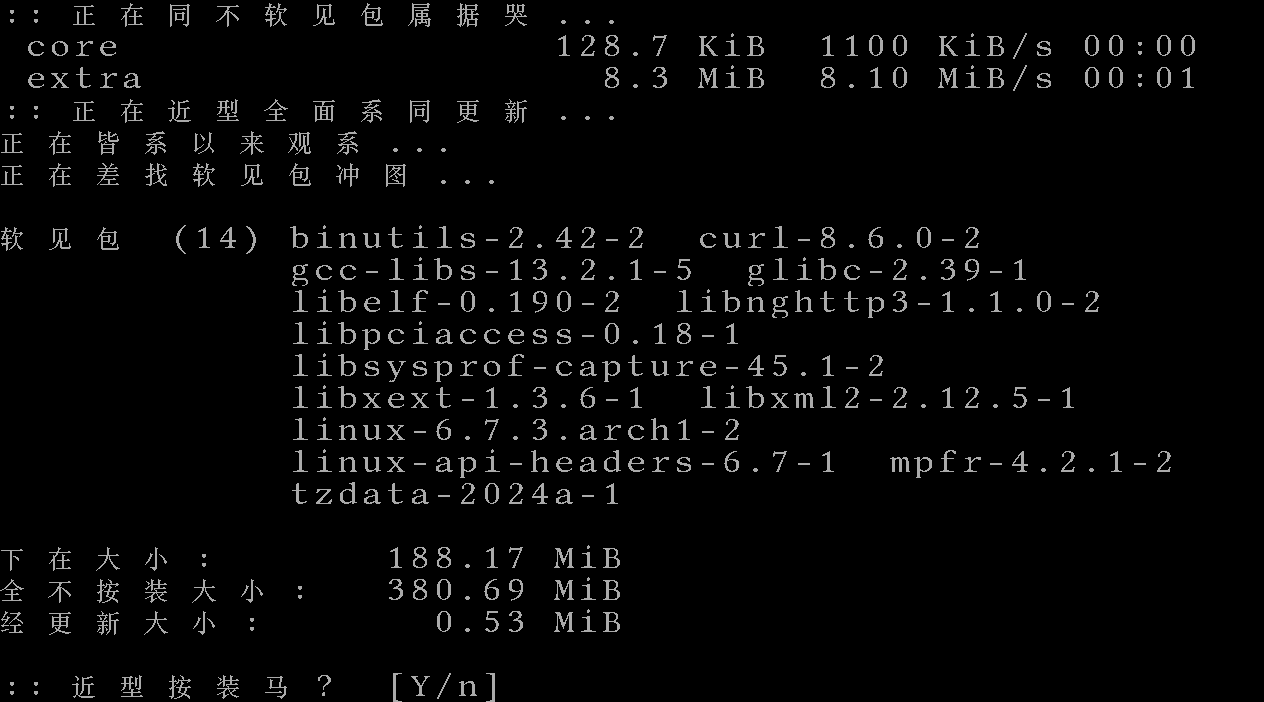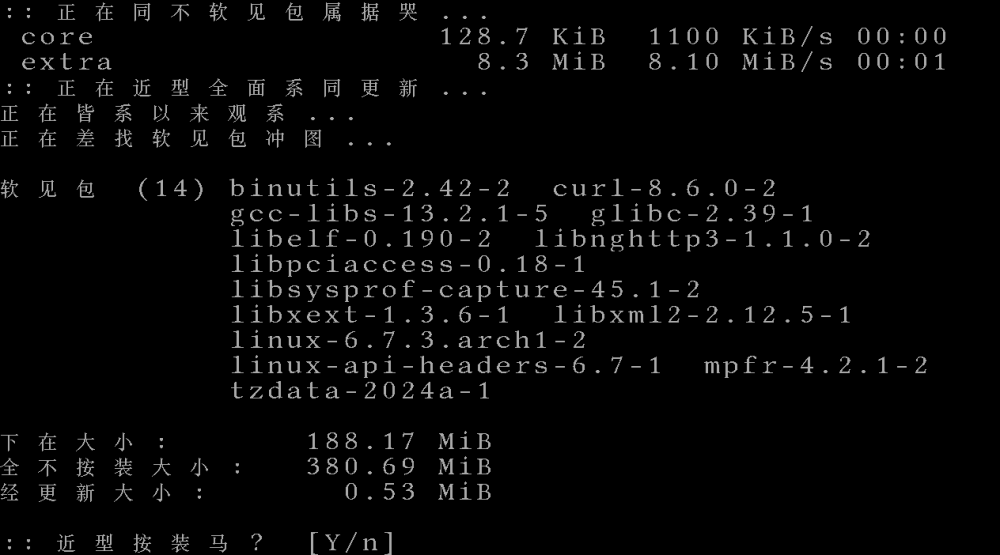
我把它作为一个练习来开发,以便更好地了解 Linux TTY 的文本渲染,或者说是一个挑战,以探索 "过时 "技术的极限。
我把它作为一个练习来开发,以便更好地了解 Linux TTY 的文本渲染,或者说是一个挑战,以探索 “过时 “技术的极限。
这是什么玩意?
Linux TTY 上的字体可以通过 setfont 实用程序(通常在 kbd 软件包中)进行更改。它最多只能支持 512 个字形,但每个字形可以映射到多个 Unicode 代码点。因此,为了支持中文,我需要在这个狭小的空间里挤出成千上万个汉字。幸运的是,现代汉语普通话只有大约 400 个不同的音节(忽略声调)。我们为每个音节挑选了一个最常用的字符,用来表示所有这几百个发音相似的字符。加上 96 个可见的 ASCII 字符和一些符号,它们完全可以容纳在 512 个字形的空间里!
但为什么要弄这个玩意?
老实说,盯着那些 “错误 “的字符猜测句子的意思并不是一件令人愉快的事情。因此,我不指望有人把它作为日常驱动程序。现在是 2024 年,你应该使用自己喜欢的 Wayland 或 X 桌面,而不是 TTY。所有主流图形用户界面工具包对中文(以及所有语言)的支持都比这个黑客软件要好得多。
我把它作为一个练习来开发,以便更好地了解 Linux TTY 的文本渲染,或者说是一个挑战,以探索 “过时 “技术的极限。
一个可能的用例是在实时环境(如 ArchISO)中执行一些维护任务。你无法访问图形桌面或打补丁的内核,只能使用 TTY,但需要检查中文文件名。你需要比 “Tofu “更好的东西,但又不想安装和配置 TTY 替代品。现在,你只需安装一个小字体,就能获得这些文件名的一些 “提示”,这可能会有所帮助。
另一个有趣的想法是,它暗示了如果第二次简化汉字方案成功,中文会是什么样子。如果第二次简化汉字方案成功,中文会是什么样子?(注:本项目使用的汉字与第二版《简繁体》并不完全相同。在该方案中,尽管许多汉字都有不同的含义和来源,但它们只是根据相似的音或形被合并了。它被认为是向汉语罗马化迈出的一步。
幸运的是,它失败了。这就是为什么我们今天仍然可以使用优雅的汉子汉语。
它是怎么做出来的?
准备字体的汉字部分。
- PSF 字体最多只能包含 512 个字形,但每个字形都可以映射到多个 Unicode 编码点。在西方字体中,这一功能允许 A(拉丁文 A)和 Α(希腊文 Alpha)共用一个字形,以节省空间。
- 在这个项目中,为了节省空间,我将所有具有相同拼音(忽略声调)的汉字映射为一个 “代表”。例如,”妈麻马骂吗”(拼音:mā má mǎ mà ma)全部映射为 “马”。汉字-拼音映射是通过脚本从 fcitx/libime 的拼音数据中提取的。
- 每个字形的位图来自一个旧的公共免费字体
gb24st.bdf。它是许可授权的中文位图字体之一,但只涵盖 GB2312 字符。 - 因此,有些拼音音节没有包含在这个项目中,如 rua(挼)、fiao(覅),因为在
gb24st.bdf中没有任何汉字的位图使用这些拼音。但不管怎么说,它们很少被使用,腾出这些空间来包含一些符号可能是件好事。 - 代表汉字基本上是挑选的该读音的最常见的汉字。不过有少数几个是我手工挑选的,目的是避免混淆或使用一个能组成许多形声字的声旁。
readbdf.py随后就读取这个列表,并将代表汉字的位图从gb24st.bdf中提取出来。输出格式为 PSF Tools 中使用的 “txt” 格式。
准备 ASCII 部分和一些其他符号。
- 它们来自 Libertinus Mono 字体。该字体为矢量字体,我使用 FontForge 将其转换到了 bdf 格式的位图字体。
- Linux TTY 假定第 32 个字形是 U+20(空格字符),否则该字形将用于清除背景。因此,我将 U+20 重新定位到第 32 位。